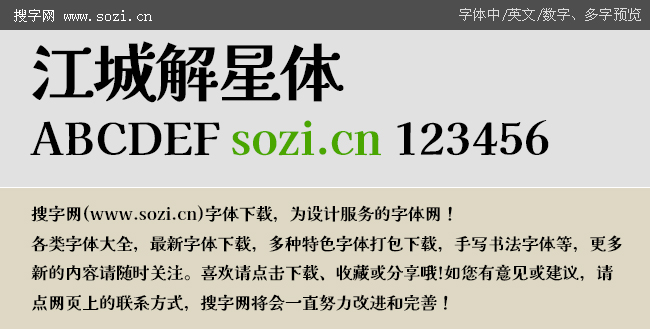
江城解星體
搜字網(wǎng)給大家提供一款江城解星體中文字體下載,江城解星體不同于傳統(tǒng)的印刷,通過在右側(cè)添加加圓型襯線,使字體左右更加平衡,同時(shí)也為字體添加了不一樣的特色。解星系列字體是日本的一款開源字體,其制作的漢字部分主要是依據(jù)日本的JIS水準(zhǔn),所以簡體字型較少,江城解星體完成現(xiàn)代漢語通用字表的補(bǔ)字,再加上原解星系列已有的簡體字部分,已經(jīng)有5498個(gè)簡體字。適用于平面宣傳設(shè)計(jì)、網(wǎng)頁設(shè)計(jì)、海報(bào)設(shè)計(jì)等應(yīng)用。